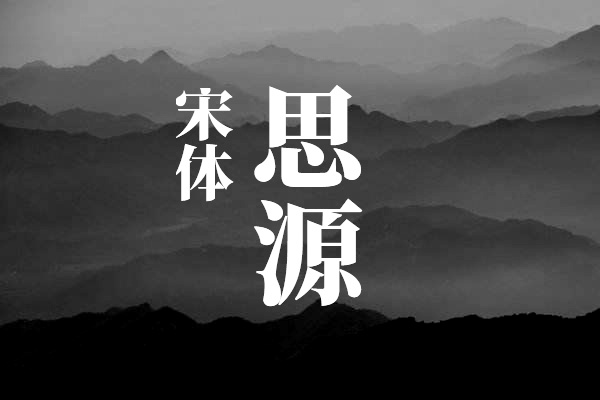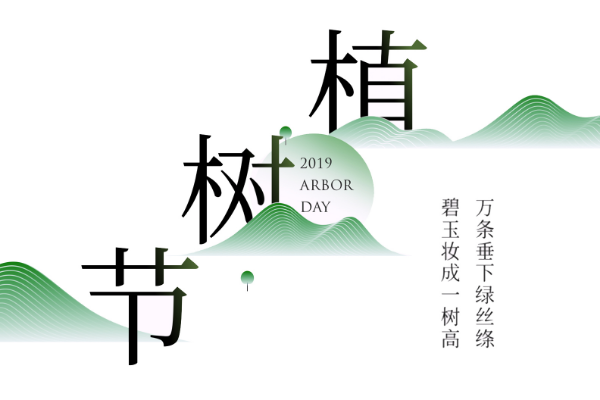
思源宋体-简体中文版
谷歌与Adobe携手推出了一款全新的开源字体——思源宋体(Source Han Serif),这款字体支持四种不同的东亚语言,包括简体中文、繁体中文、日文和韩文。为了满足各种视觉审美和排版需求,思源宋体提供了七种不同粗细形式的共65,535个字形(OpenType 格式支持的最大上限)。
虽然这四种语言的字形看似相同,但实际上可能存在四个区域的差异化字形设计。思源宋体精心设计了所有这些字形变体,并涵盖了这些区域化的字形。这意味着排版师可以更加灵活地选择适合不同区域的字体粗细和样式,以更好地满足特定的排版需求。
总之,思源宋体是一款功能强大的开源字体,支持四种不同的东亚语言并提供多种字形和粗细选择。这款字体适用于各种不同的排版场合,可以满足排版师的各种需求,使视觉效果更加丰富多样。